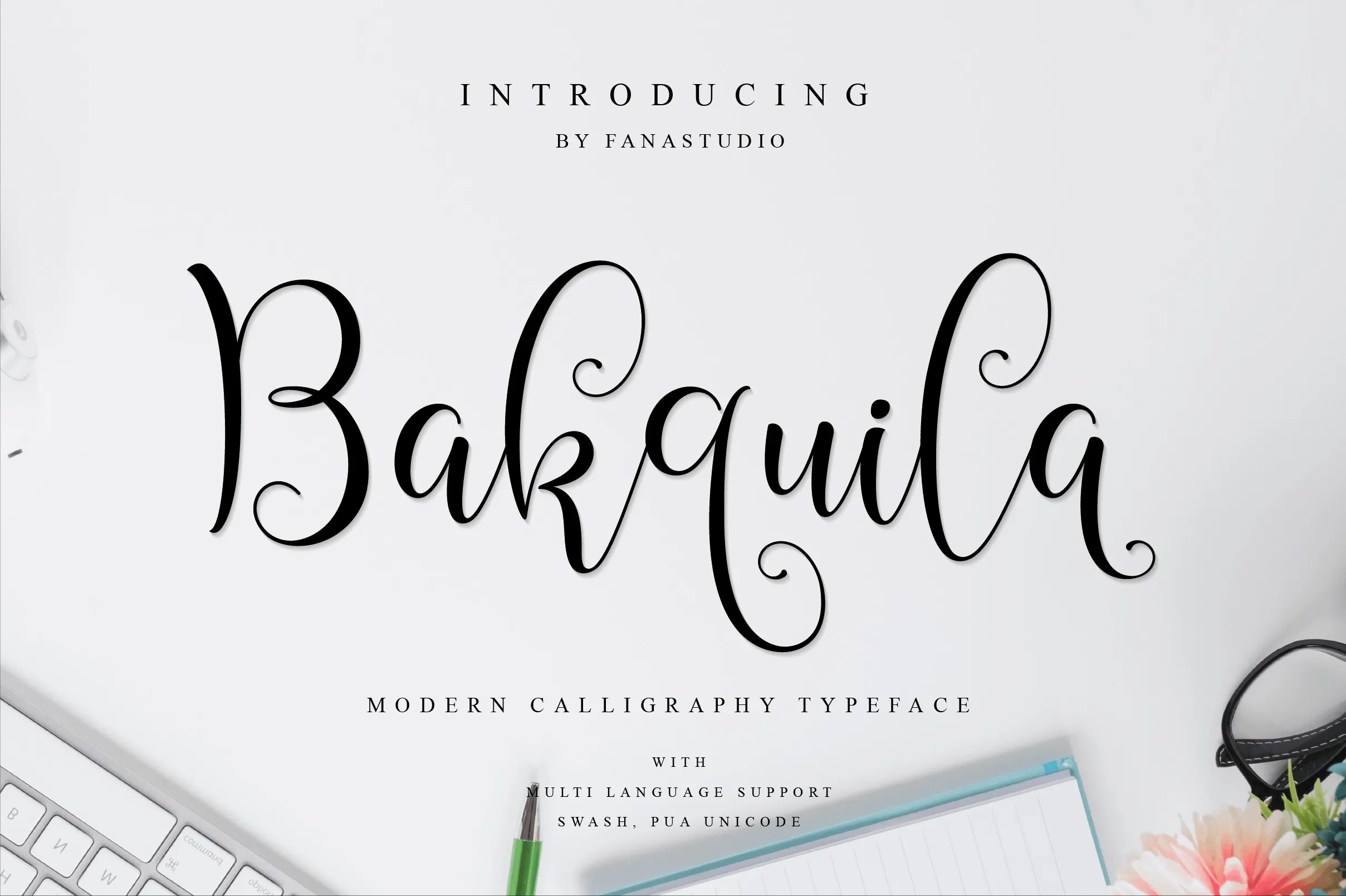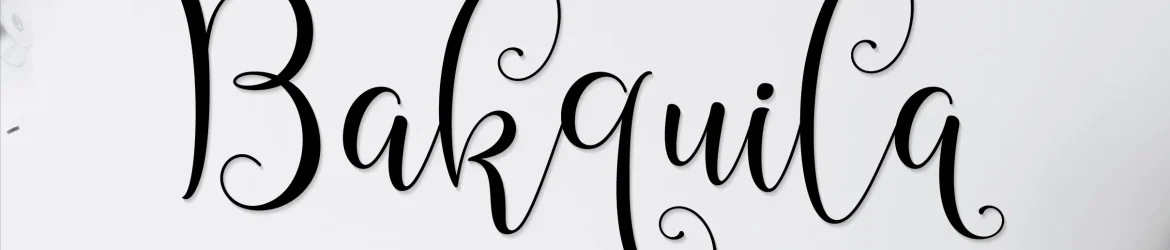
Bakquila Script Font – Download Grátis
A Bakquila Script Font é uma fonte elegante e sofisticada que traz aos designers diversas funcionalidades abertas como alternativas de estilo, formas iniciais e finais, além de ligaturas. Esta fonte perfeita para qualquer projeto gráfico, desde o desenvolvimento de logotipos até a criação de designs de wedding invitations, etiquetas de embalagem ou até mesmo watermarks. Suas versões abertas permitem que designers criem uma variedade imensa de efeitos visuais, tornando-a um recurso valioso para vários formatos de mídia digital, como redes sociais, anúncios e em conteúdo offline. Engajante e fácil de se usar, a Bakquila Script é uma ótima escolha para qualquer projeto que requer um toque elegante ou sofisticado.